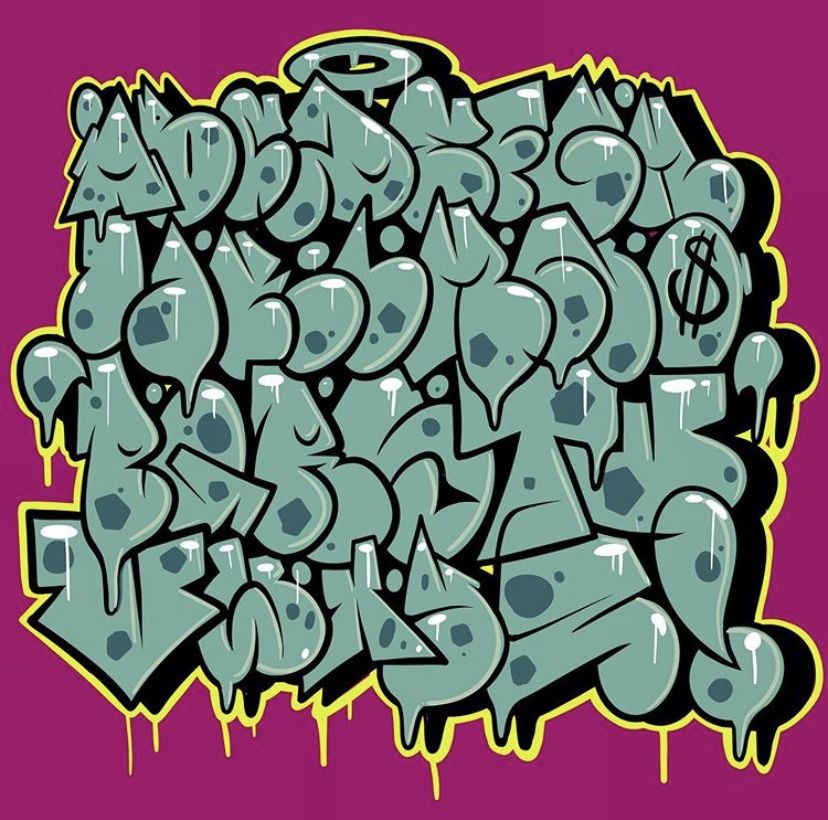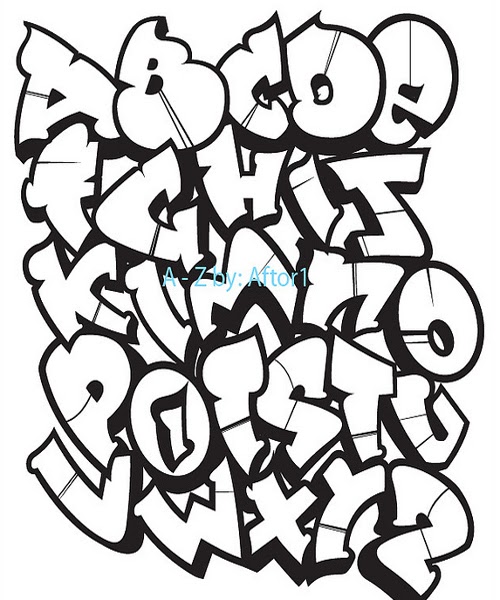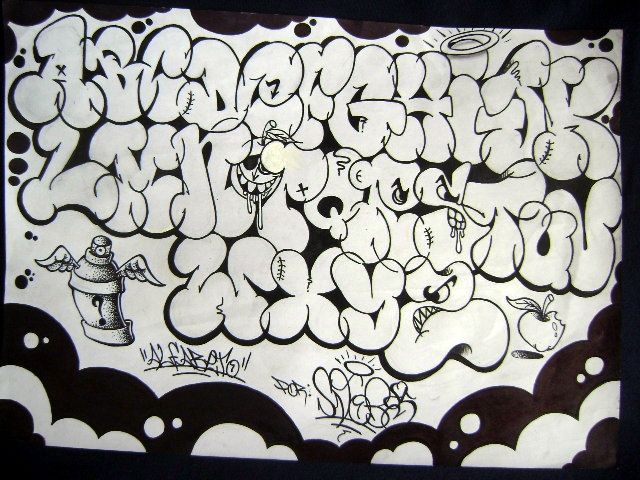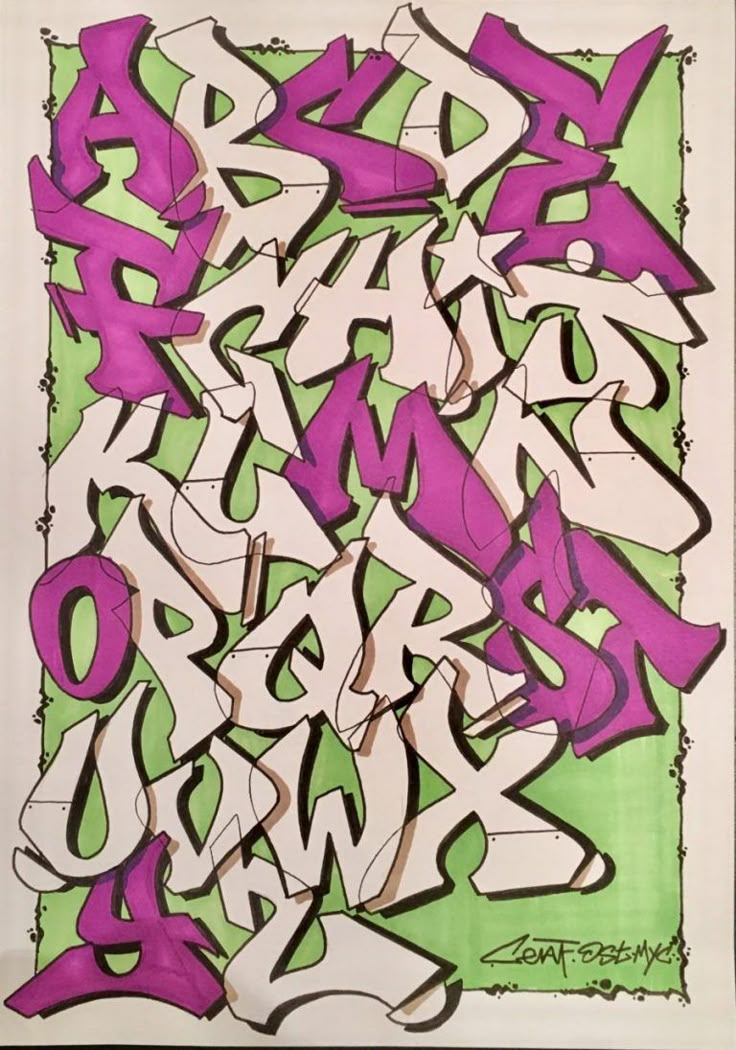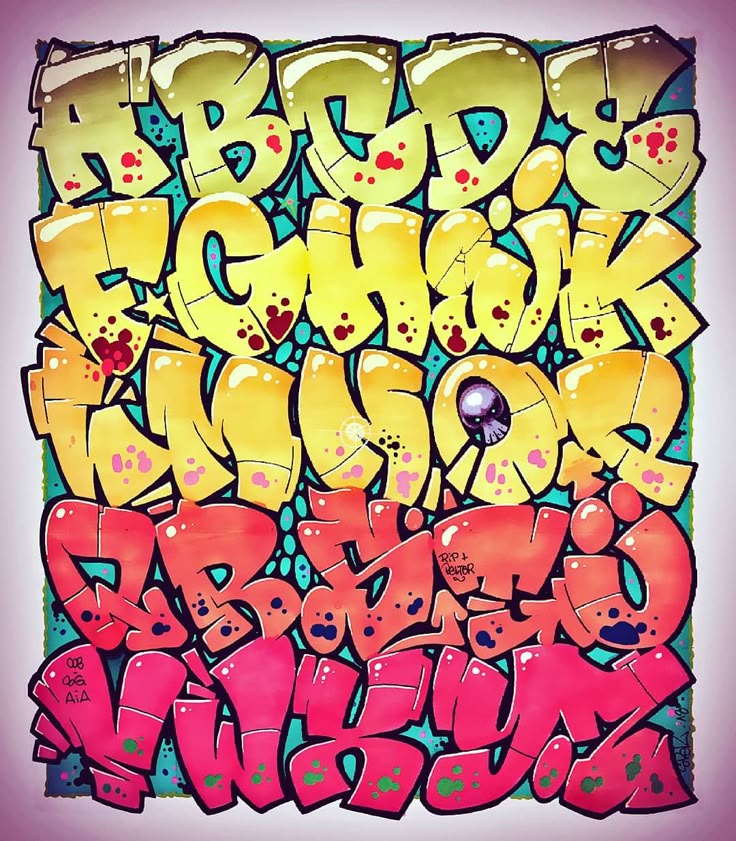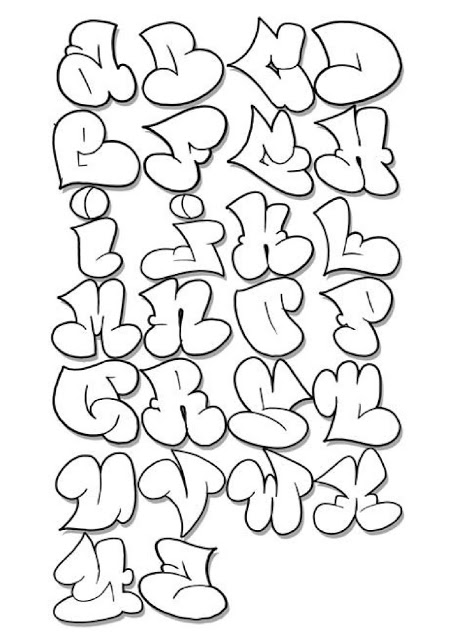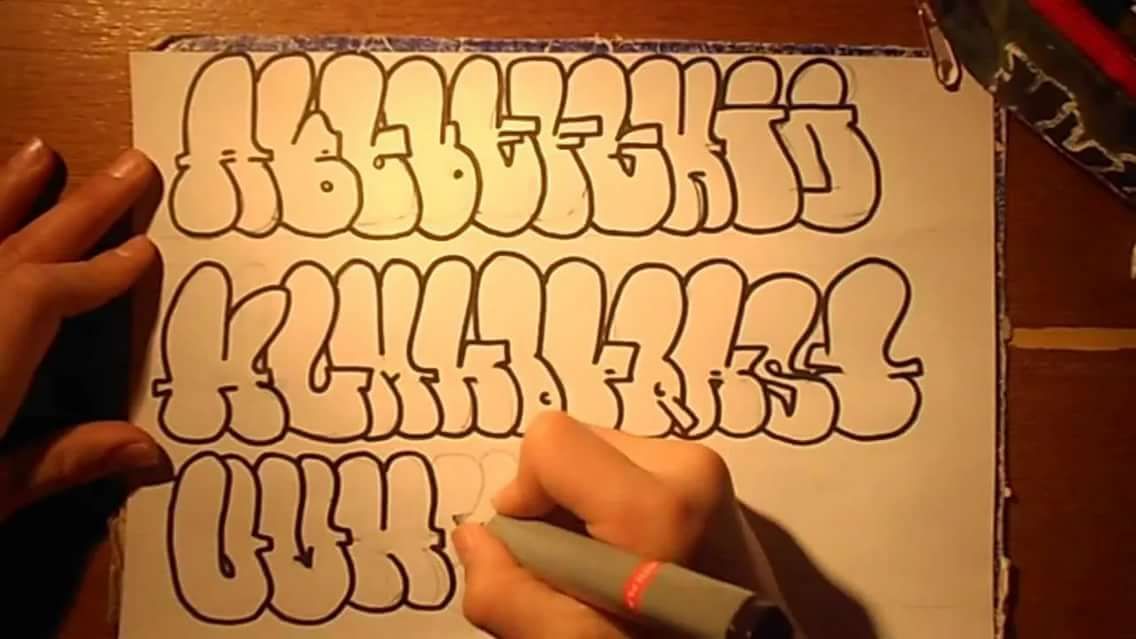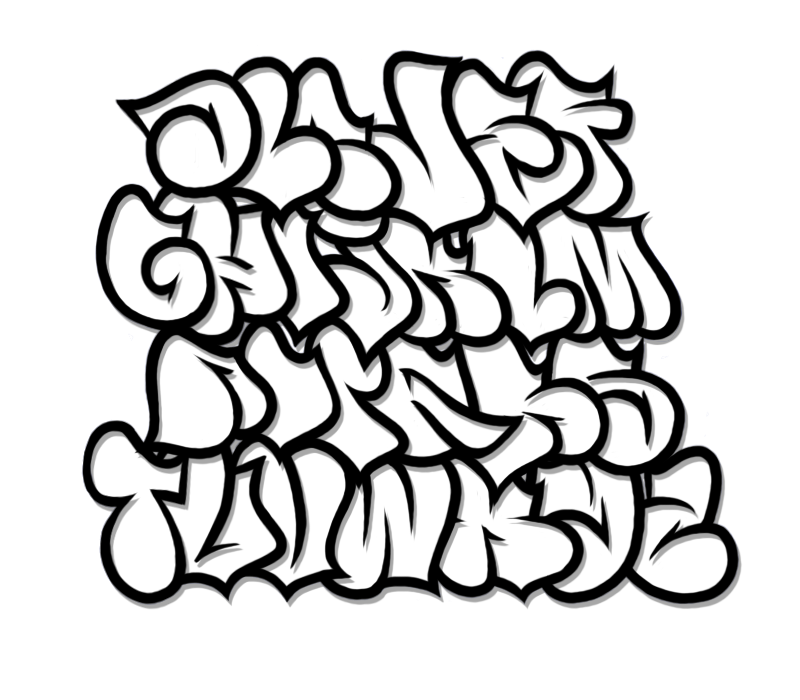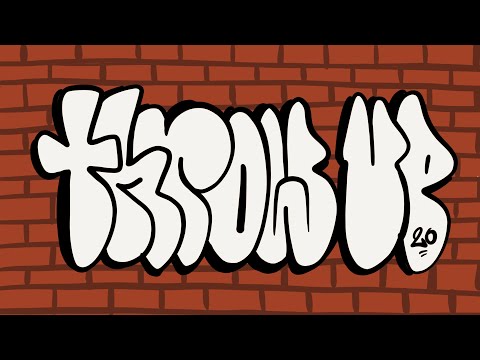
Граффити-бомбинг — Яркие примеры явления и его особенности
Бомбинг — это то, что наибольшим образом относится не к самому граффити, а к поведению художников на уличной сцене. Он основывается на распространении надписей или рисунков, которые чаще всего создаются с помощью баллончика с краской в наиболее ускоренном режиме. Никаких правил граффити бомбинг не имеет, а цель каждый представитель уличного искусства вырабатывает сам. Кто-то таким образом увеличивает узнаваемость своего стиля граффити, кто-то просто напоминает всем о своём существовании. Мы не можем исключить того, что отдельные художники таким образом компенсируют различные проблемы развития своих личностей.
Чаще всего они носят дефицитарный характер. При шизоидном расстройстве не хватает умения совершать самые обычные поступки, постоянно приходится придумывать мир заново, а при зависимом человек не осознаёт себя целиком. Различные типы личности могут выражать себя в рамках стрит-арта по-разному, но получается так, что на каком-то этапе развития бомбинг нужен почти всем.
Зачем это делается?
Название одной из российских групп стрит-арта «Зачем?» традиционно считается риторическим. Но не все подобные, почти риторические, вопросы не имеют ответа. Зачем же люди занимаются граффити-бомбингом? Для самоидентификации, определения себя, получения точек отсчёта, возвращения вечно ускользающего «я» на своё место. Во всяком случае, если речь идёт про настоящее уличное искусство.
Дополнительные цели всегда можно придумать. Они могут быть:
- коммерческими — с помощью бомбинга неоднократно пытались рекламировать различные товары, но практика показывает, что так можно не только увеличить, но и потерять популярность бренда — хорошо лишь для товаров определённой группы;
- политическими — это началось ещё в годы Парижской коммуны, и постоянно продолжалось во всех странах мира — в период революционной активности на стенах появляются работы политического содержания;
- социального протеста — почти тоже самое, что и политика, но чуть более по-философски должно выглядеть — не «долой буржуев», но «долой общество потребителей»;
криминальными — с помощью граффити уличные банды «метят» свою территорию.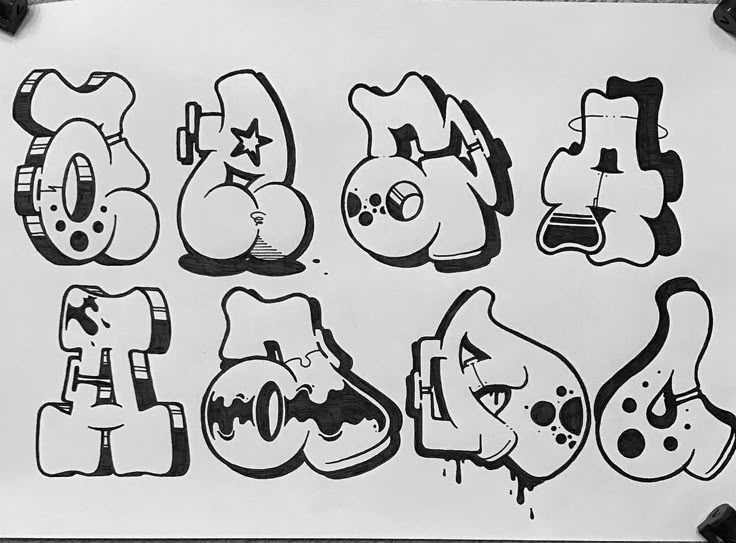
На стыке изобразительного искусства и перформанса…
Классический бомбинг оторван от всего лишнего, включая изобразительное искусство, как бы парадоксально это не звучало. Если это искусство, то 80% важности в нём имеют поступки. Настоящий бомбинг интернационален, но пальму первенства в нём держат немцы. Это группа 1UP или «Одна единая сила», которая заполнила своим тегом весь Берлин, а потом он стал распространяться и по миру. Неизвестно — было ли участниками проекта изображено хоть что-то, кроме своего логотипа. А работают они исключительно партизанскими и нелегальными способами, лишь в последние несколько лет сделали несколько вылазок на выставки и биеннале.
Как это делается?
Впрочем, лучше спросить, когда… Ночью. Да, обычно бомбингом занимаются под покровом темноты. Это похоже на боевые операции или какие-то криминальные проделки. Не совсем правильной будет постановка вопроса о том, какие шрифты используют для graffiti этого направления. Используют все возможные.
Действие порождает стиль, а он — шрифты и практические особенности их начертания. Представим себя на месте человека, который пишет тег на двери супермаркета. А бомберы иногда позволяют себя и такое. Всё нужно сделать в считанные минуты. Так возник вариант создания тегов и других надписей, который получил название throw-up, от английского глагола to throw-up – бросать или кидать. Его синонимом является термин «флоп», от глагола to flop — шлёпать или ронять. Всё это означает рисунки, сделанные на очень большой скорости. Если это буквы, то они могут состоять только из заливки и контура. Стиль определяется условиями, ничего специального.
Не всегда артисты уличной сцены имеют в распоряжении только минуты. Внешний вид вагонов в депо или стен каких-то проходов можно видоизменять часами. Поэтому в ходу извивы дикого стиля и нарочитая агрессивность шрифтового стиля «блокбастер».
Настоящее бомбинга и перспективы его развития
В настоящее время бомбинг не исчез, как это иногда думают, но лишь изменил некоторые особенности.
В Москве, несмотря на все старания властей, кто-то ещё осмеливается рисовать и писать на стенах в традиции агрессивного бомбинга даже в центре города, хоть там и установлено очень много камер наружного наблюдения.
Отношение к такому граффити в обществе всегда было полярным. Кто-то считает работы хулиганством, а кто-то видит проявлением смелости и новаторства. Многое в этом деле зависит от индивидуального подхода авторов и их умения соблюсти баланс, если не на уровне административного кодекса, то хотя бы в плане норм морали и этики.
Граффити-Бомбинг
Bombing относится к одному из самых экстремальных видов граффити. Это связано с тем, что бомберы предпочитают расписывать запрещенные или охраняемые объекты, сознательно нарушая установленные нормы. Собственно сам рисунок, выполненный в спешке на скорую руку, и называется «бомба». Для бомберов очень важно создавать свое творение на глазах изумленной и шокированной публики, таким образом формируя свой навязчивый фейм.
Нередко авторы стараются поразить воображение масштабом рисунков, предпочитая раскрашивать поверхности больших размеров.
Возникновения бомбинга своими корнями уходит в Нью-Йоркскую подземку начала 70-х гг. прошлого века, когда местные райтеры окончательно облюбовали подвижной состав метрополитена в качестве объектов росписи. Начинается настоящая экспансия на вагоны метро, которые враз оказались заполоненными вызывающими надписями.